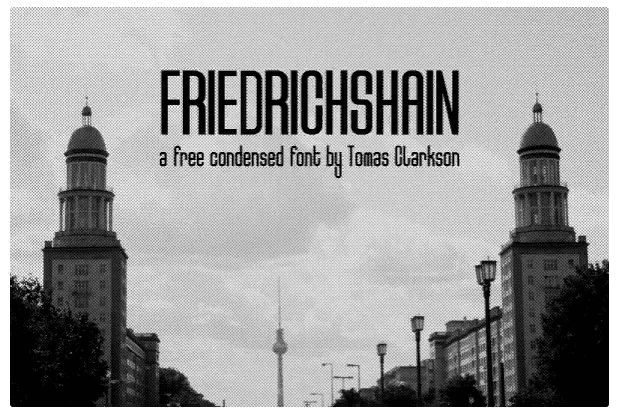
Название: Friedrichshain Font (2021)
Friedrichshain
- это конденсированный шрифт, созданный Томасом Кларксоном.
Он получил свое название от застроенного района Восточного Берлина, где доминируют высокие здания советского стиля.